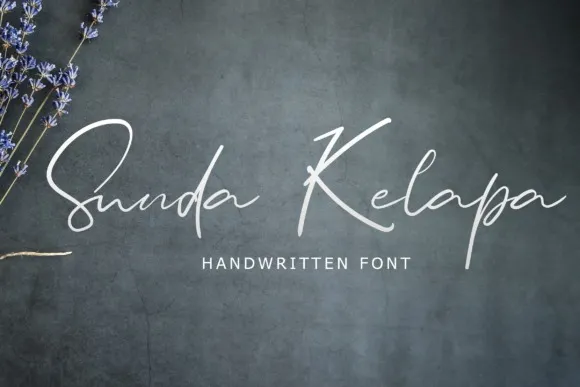
Sunda Kelapa Font – Fonte Grátis
Sunda Kelapa Font
A Sunda Kelapa Font é uma elegante tipografia círconfusa com um fluxo natural e elegante. Perfeita para marcas criados à mão buscando uma script forte com a sensação autêntica de escrita a mão. Esta fonte é perfeita para marcas que valorizam o estilo e a sofisticação, tornando-a uma escolha ideal para marcas modernas e criativas. Com seu design elegante e fluido, a Sunda Kelapa oferece um tom suave e confortável ao texto, permitindo que os designers maximizem a exuberância natural da escrita a mão em suas criações. Este é o tipo de fonte que vai transformar seus projetos digitais em algo único e autêntico.